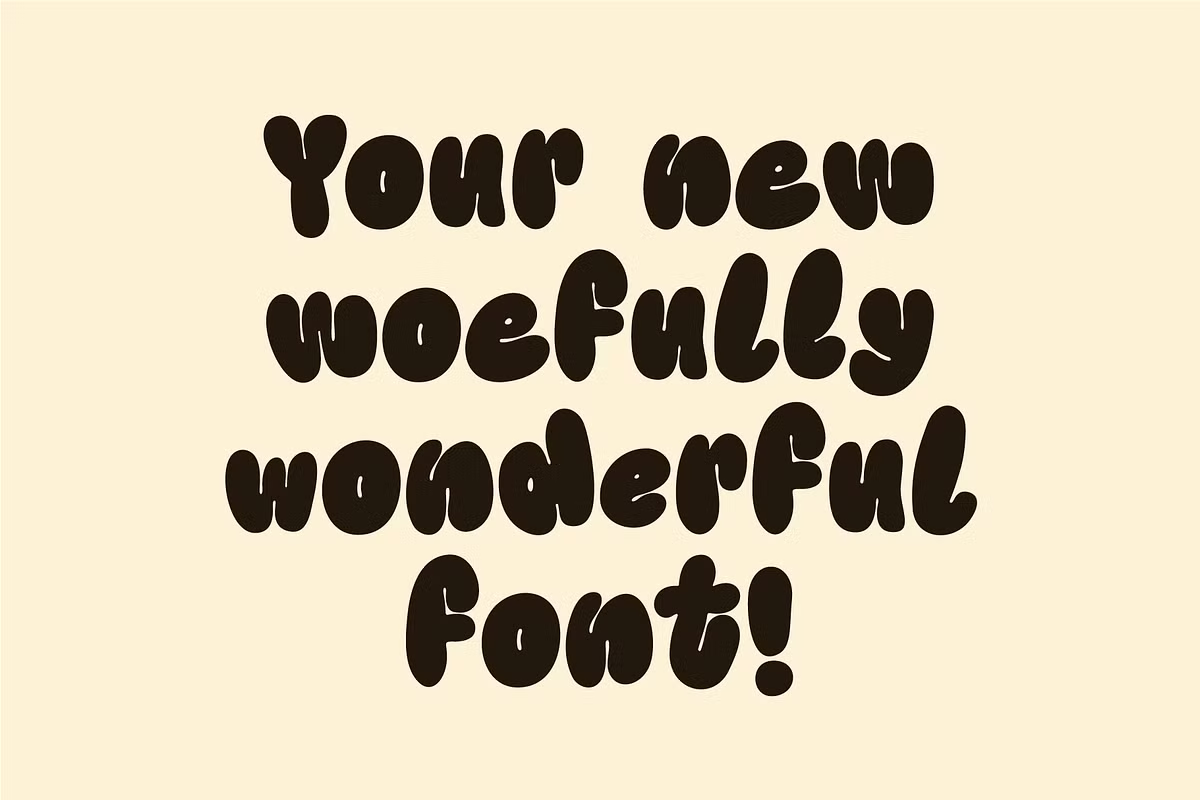
Kooky Cloud Font
Description de Kooky Cloud Font
Kooky Cloud est une police d’affichage audacieuse et amusante de Studio Funshop. Cette police est un pur art des polices de caractères écrit à la main qui a été conçue pour être aussi folle que possible – elle est originale, pétillante et tout simplement fabuleuse. Il existe des styles pour chaque lettre, avec des variations pour les majuscules et les minuscules Aa-Zz, ainsi que des formes amusantes pour les symboles comme !, ? et &. Idéal pour les logos, les citations, les œuvres d’art, la signalisation, les titres ou tout projet auquel vous souhaitez lui donner un aspect fait maison.
Il contient des lettres majuscules et minuscules (Aa-Zz), des chiffres et d’autres symboles, ainsi que toute la gamme de signes de ponctuation qui aideront à incarner l’approche individuelle du design ! Apprécier!
Kooky Cloud Régulier
Kooky Cloud Extra Kooky